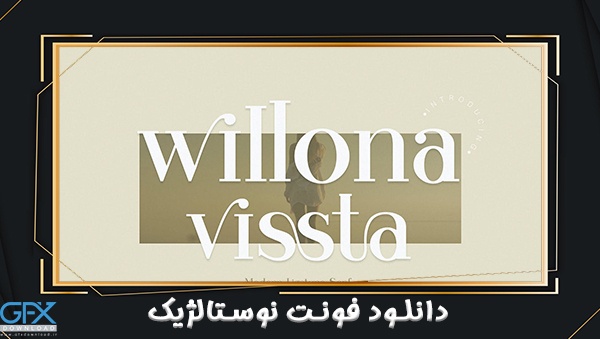
دانلود فونت نوستالژیک willona vissta یک مجموعه حروف سری زیبا و درجه یک است. این فونت هم مدرن و هم نوستالژیک است و برای لوگوها ، مجلات ، رسانه های اجتماعی عالی عمل می کند. در حال حاضر مطابقت داشته و آماده استفاده با هم برای طراحی بعدی شماست! دانلود فونت نوستالژیک willona vissta برای آن دسته از شما که برای طراحی های خود نیاز به ظرافت ، شیک ، درجه یک ، شیک و مدرن دارید .
دانلود فونت انگلیسی نوستالژیک willona vissta
فونت willona vissta با ویژگی های OpenType ساخته شده است و شامل پیوندها ، اعداد ، علائم نگارشی است و همچنین از زبان های دیگر پشتیبانی می کند.